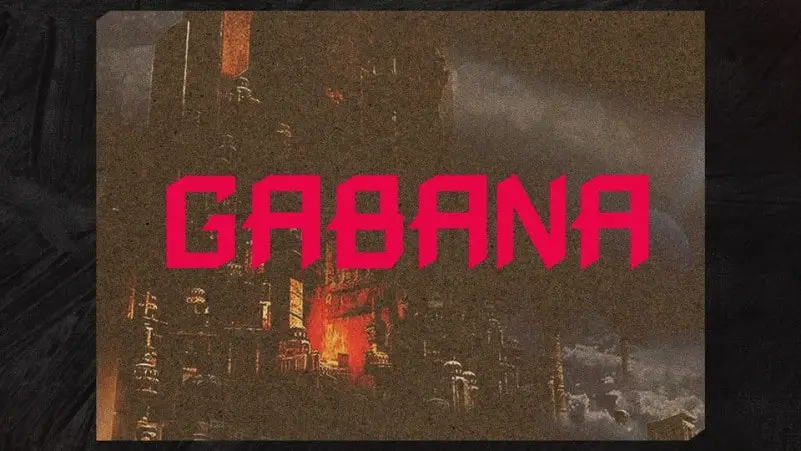
Gabana Display Font Family é uma família de fóruns de estilo display única e interessante que se destaca para projetos criativos futuros. Originária do design tipográfico dos anos 80, essa fonte incorpora elementos modernos e clássicos com formas letrais grossas e letras cortadas limpas. O nome Gabana, de origem africana, significa “um menino com coragem e determinação”. Esta família de fóruns é uma excelente opção para criar designs dinâmicos que expressam coragem e determinação, perfeita para aplicar em elementos visuais como títulos de página ou design gráfico. Com Gabana Display Font Family, transforme suas criações com um toque de criatividade e personalização.